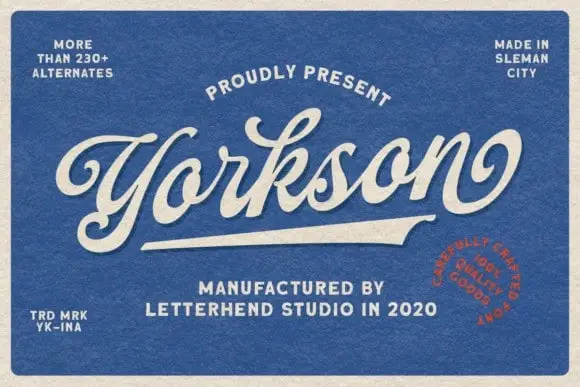
Yorkson Script Font – Download Grátis
A Yorkson Script Font é uma elegante e original fonte multitalentosa desenvolvida pela designer letterhend. Esta tipografia apresenta um toque retrô estiloso, perfeita para criar invocações de casamento, cartões de agradecimento, frases de encorajamento, cartões de boas-vindas, logotipos e cartões de visita, sem mencionar qualquer outra design que possa precisar de um toque feito à mão. O destaque é o uso de alternativas estilizadas e swashes na fonte, tornando-a ainda mais atraente e interessante para seu projeto. Este script é perfeito para complementar qualquer design gráfico, oferecendo uma graça única e sofisticada que certamente não será esquecido.